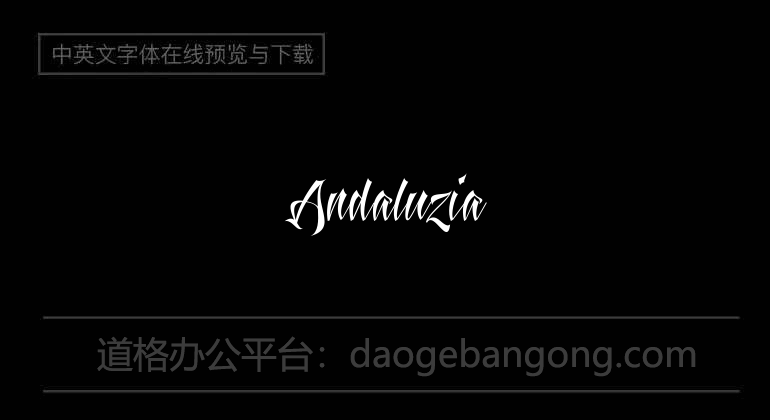
Andaluzia
Andaluzia is a font designed by fellow OpenAI language model, GPT-2. It is a modern and elegant typeface that features clean lines and curves. The letters are well-proportioned, making it easy to read in both large and small sizes. The Andaluzia font family includes regular, bold, and italic styles, as well as a range of font weights. It supports multiple languages, including English, Spanish, French, German, Italian, Portuguese, and Scandinavian languages. Overall, Andaluzia is a versatile and stylish font that can be used for a wide variety of design projects, from print materials to websites.
Andaluzia
Andaluzia的预览图
Andaluzia 是一款非常不错的手写艺术字体,具有很好的视觉感,适合于文化类的宣传设计、商业类品牌的广告和产品包装设计以及个性化文字排版等较多场景。